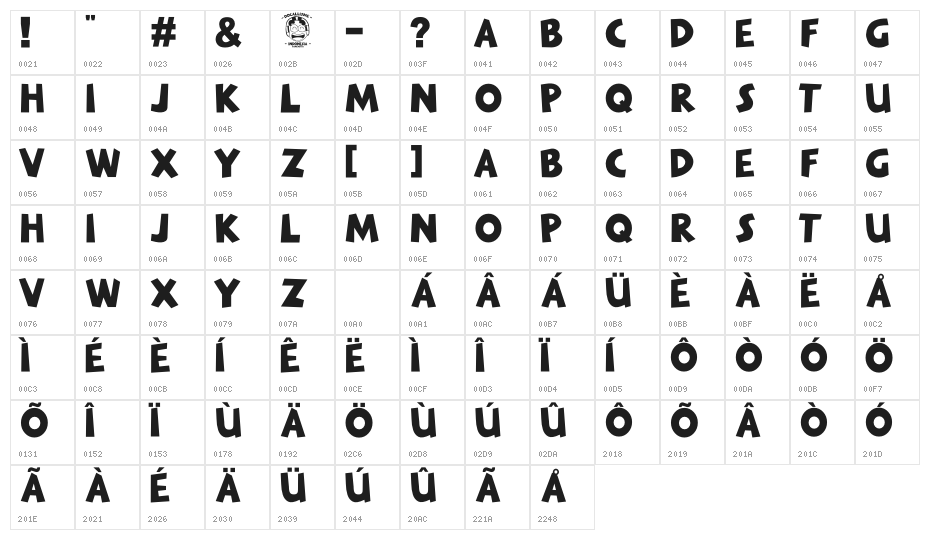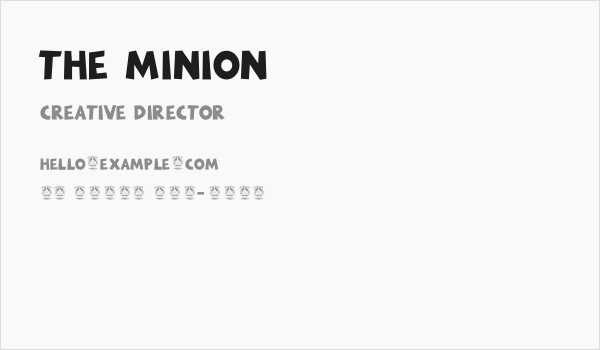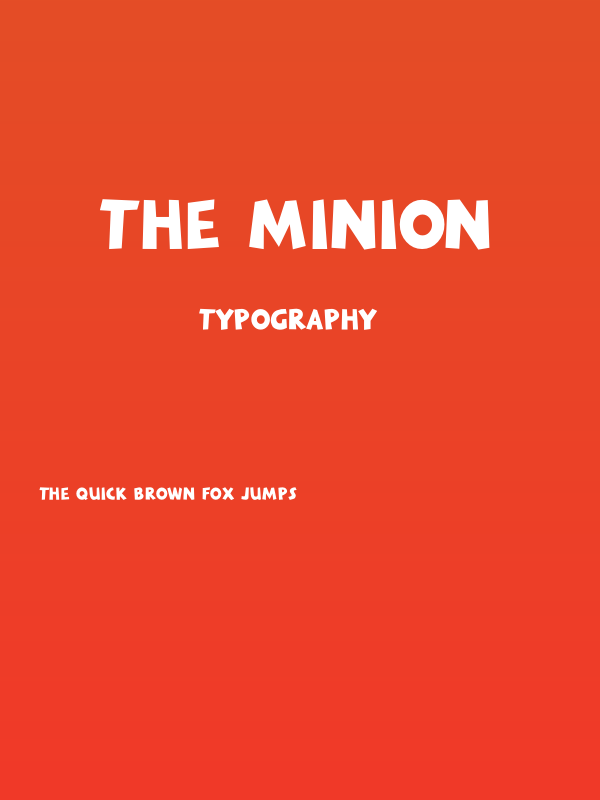
THE MINION Font
| 整体风格 | Playful, Cartoon-like |
| 推荐项目 | Ideal for children's books, comic strips, playful branding, and any project needing a fun, engaging typeface. |